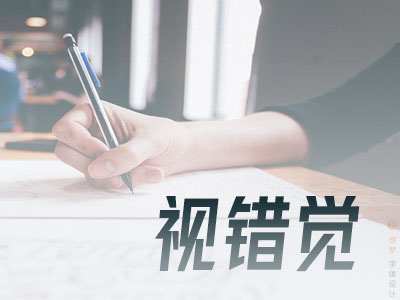
原来用了这么久的参考线是错的!字体设计中的几何错视
古人教导我们“耳听为虚,眼见为实”,真的是这样吗?并不尽然,在平面设计中尤其是字体设计中,眼见到的并不一定真实,因为有视错觉在作祟!
一、视错觉是怎么产生的?
我们看到的事物,其实并不是事物原原本本的样子,而是基于经验或参照进而形成的判断和感知。说白了就是事物本身是客观的,但我们眼里的事物却是主观的。
视错原理就是指,观察者在客观因素干扰下或者自身的心理因素支配下,对图形产生的与客观事实不相符的错误视觉感知。
在设计中这种现象很常见,比如说,同样大小的圆,被较小的圆围绕后看起来大,而被较大的圆围绕后看起来就显小。
这就是为什么设计师画参考线、打方格忙活半天,严格规整设计后,发现设计出来的视觉效果反而不理想。因为你是按照几何方法设计的,当然在视觉上有偏差啦!
无论是平面设计还是字体设计,我们的作品都是给人看的,也就是要满足视觉上的要求,所以严格按几何方法设计实在却并不实用。
尤其是字体设计,因为汉字是横竖撇捺折等等构成的,都是线条和点,甚至是块面的复杂构成,很容易产生视错现象,这就要求设计字体时,在几何造型手法的基础上,充分考虑到视觉效果。
二、视错觉在字体设计中的应用
设计字体你可以有自己的freestyle,但基本的设计原理都不懂那什么style都白搭,so,视错觉在字体设计中的应用赶紧学起来!
如你所知,汉字是由笔画、部首和汉字三个层次构成的,而平面设计又讲究的是点线面构成,所以,小梦就从点线面的维度来解析视错觉在汉字这三个层次中的应用。
壹——点的视错处理
数学老师教导我们,没有长、宽、厚只有位置的几何图形就是点,但平面设计中的点和此不同,是有面积的,点放大就成了面,实的是点,虚的也可能存在点。
1.字体重心处理
几何中心就是典型的虚点,或者称为假想点,因为汉字是方块字,几何中心就是其对角线的交点。但在方块面积中我们的视觉中心点往往不在几何中心,而在几何中心略偏左上的位置。
没错,视觉中心就是汉字重心,我们常说的字体重心其实就是对汉字几何中心的视错处理。因为重心是汉字的视觉中心,同样高矮的汉字,重心偏上的字看起来会更高些。
2.密集点画处理
一个汉字中如果有很多点,看起来就会显得比较零碎和分散,这就要恰当处理这些点画的布局和造型。在视觉上,如果点是这样分布的,就会产生视错觉现象:
所以,单独那个点的位置要特殊处理,如“消”“淡”“沙”等字,点画处理不好很容易让字看起来散架。
贰——线的视错处理
汉字是方寸之间的艺术,横竖撇捺的笔画自然很多,而线条也是很容易产生视错的,所以掌握线条视错现象在字体设计中的应用很有必要。
1.横竖粗细处理
不是有意伤害胖友们,但事实上就是这样,同样身高的两个人,胖子看起来矮,而瘦子看起来高。横竖笔画也有同样的视错现象,所以很多字体都会进行横细竖粗的处理,从而到达视觉上的平衡。
同样的,当遇到多横或多竖排列的笔画时,要恰当处理粗细和长短,横的粗细和竖的长短不要都等同。否则多横的字会看起来很宽,而多竖的字会看起来很高。
2.横竖相接处理
两条长度相等的横竖线,丁字相接后,竖线看起来会比横线长,交接点越往边缘移动,二者的长度看起来越接近。
所以处理横竖相接的笔画时,竖向的笔画尽量不要太长,而横向的笔画需要适当增长,还可以改变垂足的位置或是加粗竖变细横。
3.横竖分割处理
这种场景有种菜刀剁大葱的既视感,就是多条竖线被贯穿的横线分割后,竖线之间的间隔距离看起来会变大。
也就是说,处理这种横竖分割的情形需要根据视觉习惯减小竖线之间的间隔距离。
4.横画长短处理
横画的长短除了受到本身长度的影响,还会受到两端折线的影响,两端折线向外倾斜程度越大横线看起来就越长。
所以,在处理横画起落有衬线的情况时,横画的长短可以根据视觉感知适当调整,而不是机械的弄成等长了事。
当横画是梯形状,几个排列时上面的横画看起来会比下面的长,要注意调整。
你不会想到,其实横画的长短还会受到周围横画的影响,周围笔画长会显得中间的笔画短,而周围的笔画短则显得中间笔画长。
排列或包围影响视觉感受,这其实是很容易产生视错觉的一种现象。
5.竖画长短处理
类似的,如果竖线与两条斜线相接,这两条斜线形成的夹角越大,竖线就看起来越短,反之则越长。
说白了就是字体设计中遇到这种情况,要注意竖画和相接的两条斜线夹角的微妙关系,二者是相互影响的。
6.斜线相交处理
身正不怕影子斜?图样图森破,影子斜了身子也会歪!就像一条斜线和竖线相交,竖线越宽,斜线的错位感就越强,看起来就不像一条连贯的斜线了。
那怎么办?遇到这种情况当然是“将错就错”了,就是设计时你处理成错位的,看起来就连贯了撒,当然,也可以调整相接的笔画来处理。
叁——面的视错处理
如果说点、线的视错是针对字体内部笔画的处理,那面的视错觉就是针对汉字整体和汉字与汉字之间进行结构的调整和把控。
小梦之前在汉字的形体结构和造型以及中宫的相关内容中讲解过,为了让字看起来整体协调,设计字时通常会根据汉字的外形轮廓,把字归纳为几种几何图形然后有针对性的调整,这其实就是针对汉字在面维度上的视错觉处理。
因为大多数汉字是方块外形,我们就以方形作参考来探讨下这些特殊外形轮廓字的视错觉处理。
1.正方形
你可能不知道,正方形本身就是有视错觉的,高度略矮的矩形看起来才更像正方形。这就是为什么字体设计中明明横竖的笔画等长,字却看起来不是正方形的原因。
除此之外,同样大小的两个正方形如果其中一个中还嵌套有正方形,那么这个正方形就会看起来比较小。
其实,只要是正方形中有东西填充,看起来就会比空的正方形小,方框中的空白区域越少,整体就看起来越小。所以在处理如“日、囚、国、圈”等字时,内白少的外框尽量稍微扩大以弥补视觉上的不协调
是不是感觉自己知识丰富的像本教科书?别骄傲,正方形的视错觉还有一点,和圆形、三角形以及菱形比起来,正方形看起来是面积最大的,所以,遇到包围结构尤其是全包围结构的字,外边框要适当收缩,减少膨胀之感。
2.圆形
圆的特点是没有棱角,四周封闭,视觉上给人以旋转、运动和收缩的审美趣味。和正方形类似,直径相等的两个圆,同心圆看起来比单个圆看起来小。